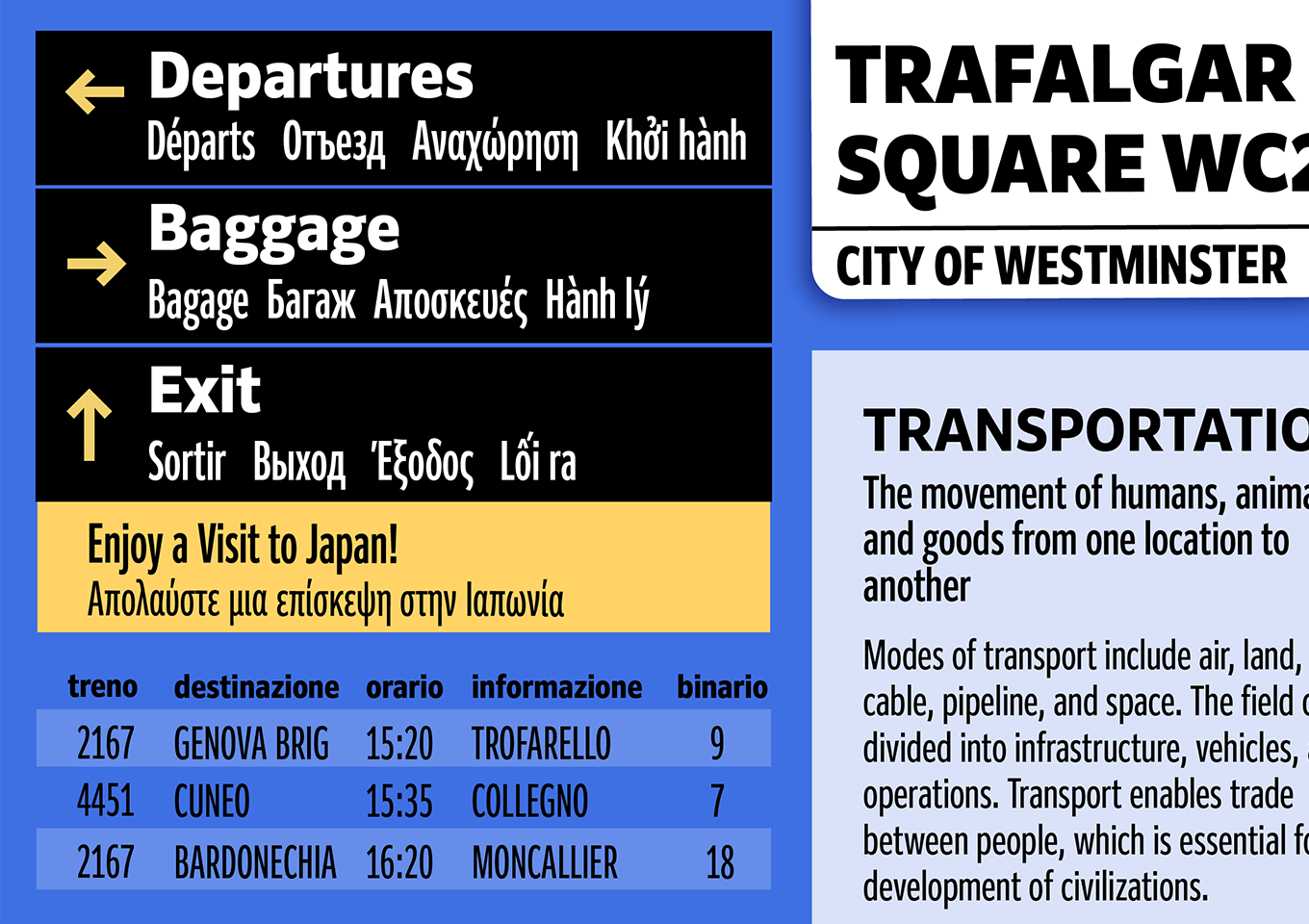
可読性を重視したシンプルで汎用性の高いサンセリフ「Clarimo UD PE」のコンデンス書体です。コンデンス書体は、限られたスペースにより多くの情報(文字)を、視認性・可読性を損なうことなく表示することを目的につくられた書体です。和文、簡体字、繁体字およびハングルをカバーする「UD新ゴ」シリーズとの併用で高い親和性を発揮します。 長体率はNarrow / Condensed / Extra Condensed / Compressed / Extra Compressed の5段階で、それぞれ8つのウエイト展開です。本文から見出しまで幅広い用途でご利用いただけます。
PE(151言語をサポートする独自規格)